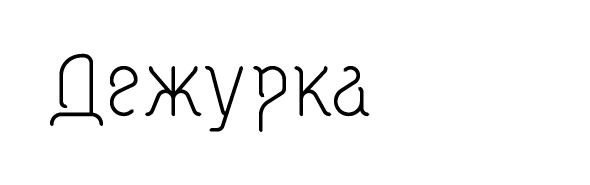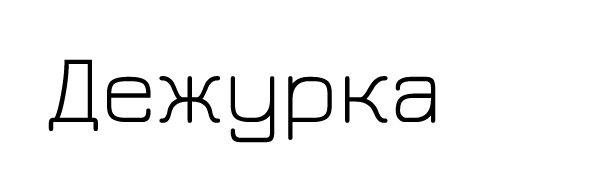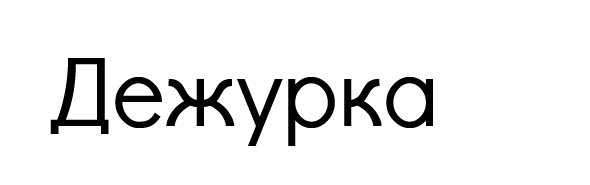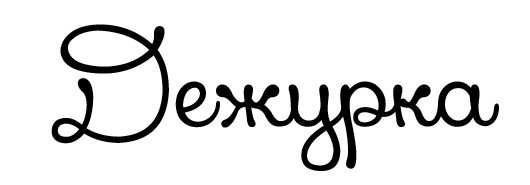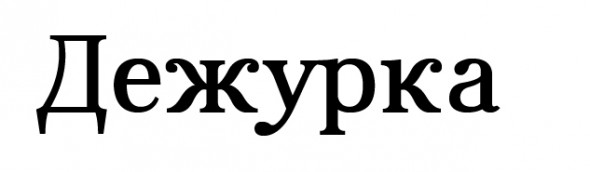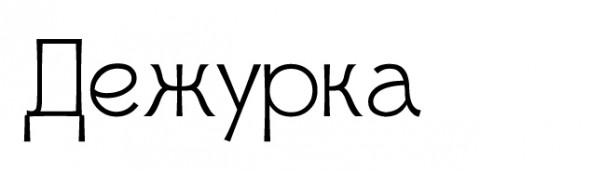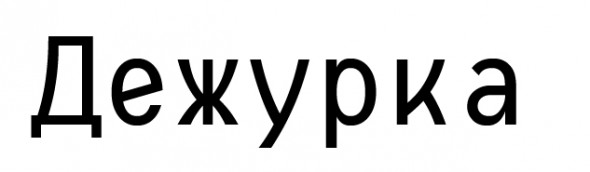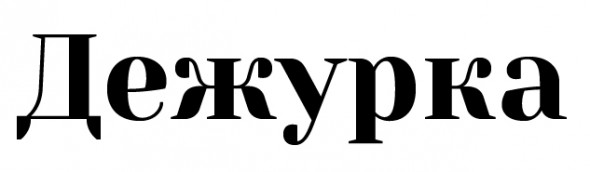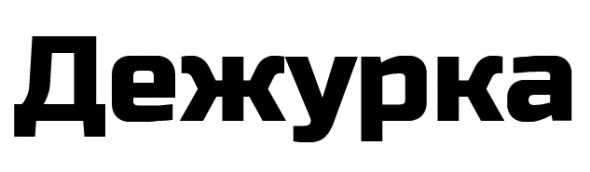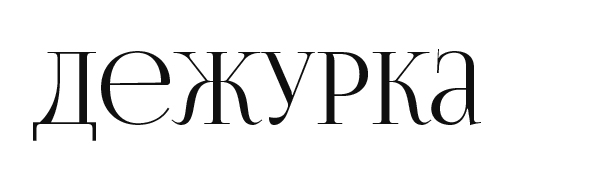
Новые бесплатные кириллические шрифты
Сегодня предлагаем пополнить ваши запасы шрифтов новыми кириллическими шрифтами. Увы, новые кириллические шрифты появляются не так часто по сравнению с латинскими. Но все же, надеемся, что в скором будущем мы сможем пополнять наши библиотеки новыми красивыми шрифтами намного чаще. Ну а пока, пролистайте этот список и, возможно, вы найдете для себя нужный новый шрифт.
YESEVA ONE
VETKA free font
Jura
Ruslan Display
Consola Mono font
Didact Gothic
FoglihtenNo06
Xiomara font
Connie font
Mikodacs font
FoglihtenNo06 font
ZnikomitNo24
Glametrix font
Yokawerad font
Aver font
Whipsmart font
Шрифты от Ivan Gladkikh
Yeseva
Russo free font
Шрифты от MRfrukta
Kánkin© FREE FONT
TETRA© FREE FONT
Silverfake© Free Typeface
Idealist Sans
Kelson Sans
Понравился только Deduct Gothic и Russo Free Font
Если нужны действительно новые — рекомендую Idealist Sans, Kelson sans.
Russo free font больше всего понравился!
Ничего особенно не понравилось. yeseva мог бы быть ничего, но «угол» в очке а как-то напрягает
Yeseva — отличный!